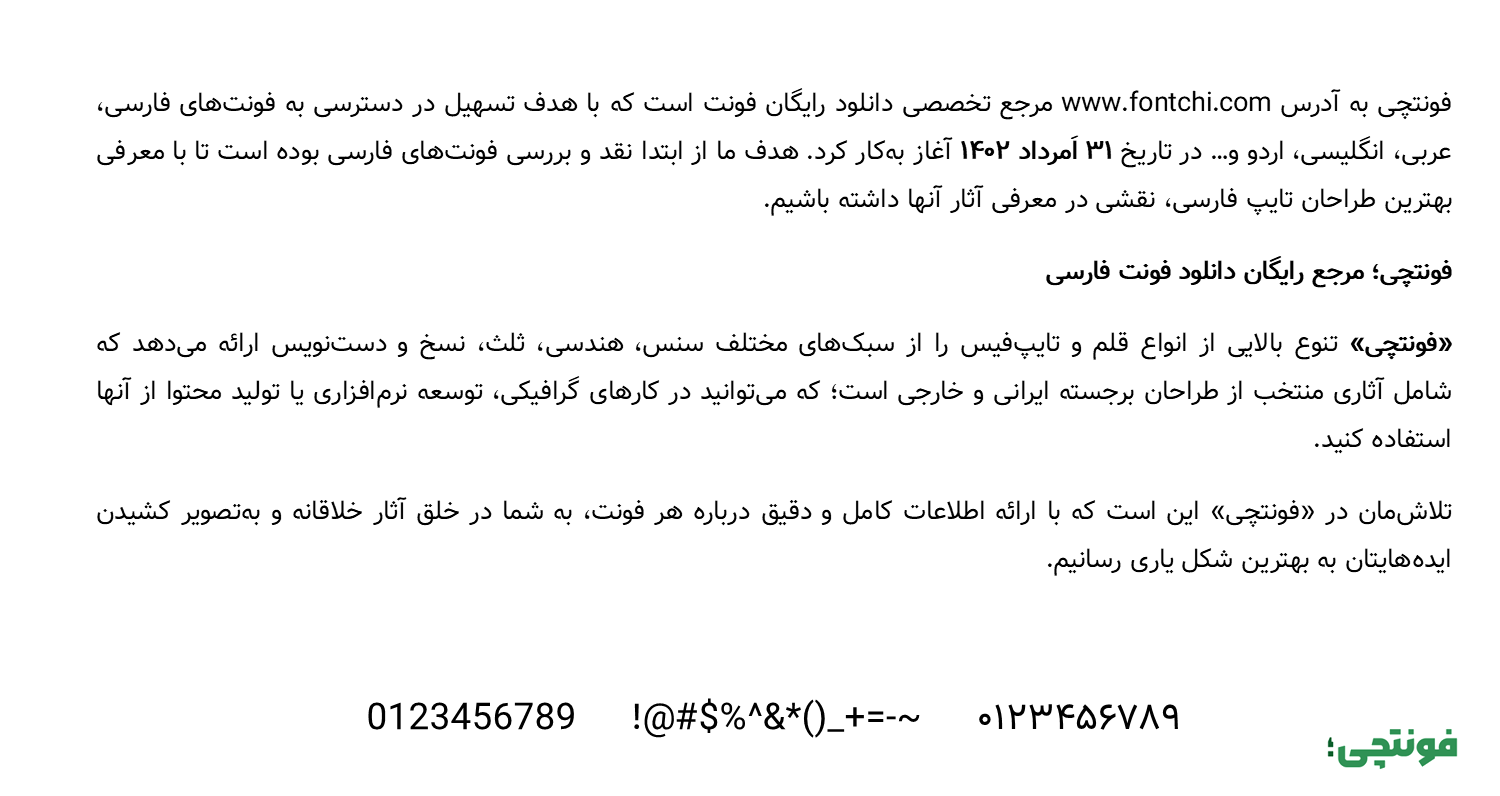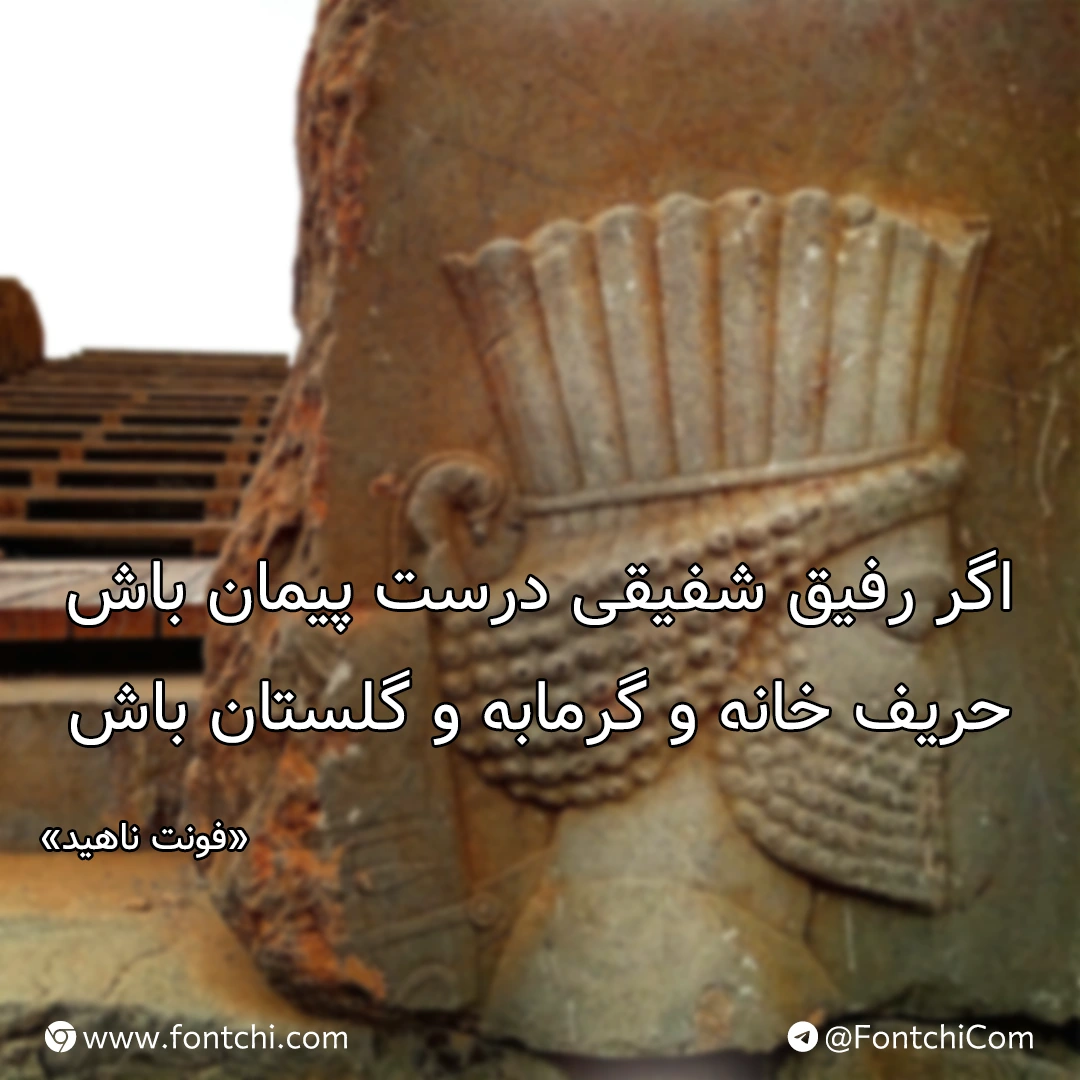
فونت ناهید (Nahid)
فونت ناهید (به انگلیسی: Nahid) که پیش از این با نام فونت میرزا نیز شناخته میشد، قلمی به سبک سنس و برگرفته از فونت دژاوو است که با هدف افزایش خوانایی متون فارسی طراحی شده است. فونت رایگان ناهید دارای یک وزن معمولی است که برای استفاده از متون طولانی توصیه میشود.
در ادامه به نقد و بررسی این فونت رایگان خواهیم پرداخت و با معرفی ساختار و ویژگیهایی که این قلم دارد، محیطها و موضوعاتی که میتوانید از این قلم استفاده کنید را با هم مرور میکنیم.
معرفی و دانلود فونت ناهید رایگان (Nahid)
فونت ناهید دارای یک وزن معمولی Regular است. در طراحی این فونت حروف دارای نرمی خاصی هستند و ساختاری به سبک خط سنس را در خود حفظ کردهاند. چشمی حروف دارای ظاهری سهگوش و گرد شده هستند که در کنار زاویهای که به شکستگیها داده شده است، ساختار فونت را تا حدودی صمیمی کرده است.
دندانهها و گردیها بهشکلی هستند که در حالت میانه خط کرسی قرار میگیرند. از همینرو با فونتی مواجه هستیم که برای استفاده در متون طولانی و بلند خوانایی لازم را فراهم میکند.
فونت ناهید از زبان فارسی پشتیبانی کاملی دارد و بهواسطه رسمخط یکسان زبانهای خاورمیانهای، برای استفاده در متون عربی، اردو، کوردی و ترکی نیز قابل استفاده است. هرچند که ممکن است در برخی زبانها به این دلیل که توسعه این پروژه در نسخههای اولیه متوقف شده است، برخی گلیفها را در خود نداشته باشد.
فونت Nahid انگلیسی نیز دارای طراحی اختصاصی نیست. برای حروف لاتین این تایپفیس از فونت تاهوما وام گرفته شده است. به همین جهت برای استفاده در زبانهای لاتین متعددی بهسادگی میتوانید از این قلم استفاده کنید. بنابراین فونت فارسی ناهید برای استفاده چندزبانه فارسی با سایر زبانهای لاتین گزینهای مناسب است.
با شخصیتی که فونت رایگان ناهید دارد، میتوان از این قلم در محیطهای مختلفی همچون مطبوعات برای روزنامه و مجلات، فونت متن کتابها و بهطور کلی هر جایی که الزام به داشتن فونتی با خوانایی بالا برای متنهای بلند احساس میشود استفاده کرد.